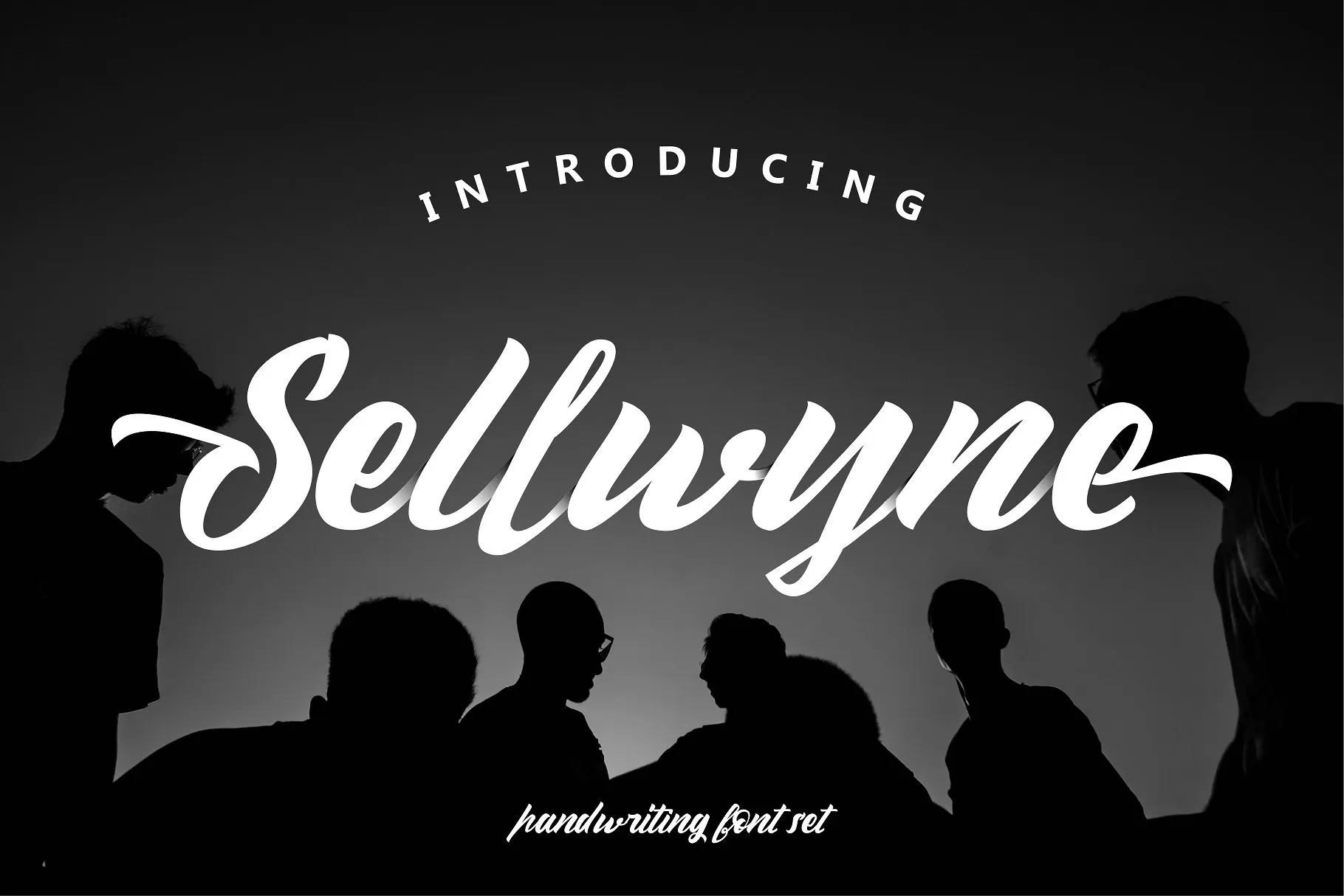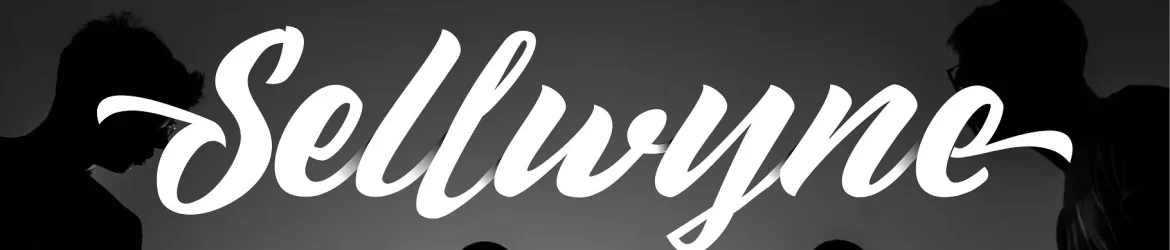
Sellwyne Script Font – Download Grátis
A fonte “Sellwyne Script” é uma escolha perfeita para quem busca expressar a autenticidade na tipografia. Criada com base no estilo do real traçado humano, esta fonte escrita à mão oferece flexibilidade e originalidade ao seu trabalho de design. Transforme simples textos em trabalhos artísticos únicos, combinando diferentes estilos como quiser. Esta font é especialmente apropriada para uma variedade de projetos, desde customização de camisetas e criação de marca até designs de casamento e publicidade. Ela também é excelente para ambientes digitais onde se espera que a escrita seja autêntica, como posts nas redes sociais ou materiais promocionais. Além disso, o Sellwyne Script é perfeito para criar letravers, fotografias de arte, marcas de produtos e sobres. Sempre mantendo aquela sensação quase pessoal que a autenticidade da escrita à mão cria em qualquer trabalho. Com esta fonte criada por Garisman Std, você tem o poder de transformar simples textos em obras de arte. Adote esta font se está procurando por uma maneira fresca e autêntica de trazer sua marca para a frente com um toque pessoal que destaca seu trabalho.